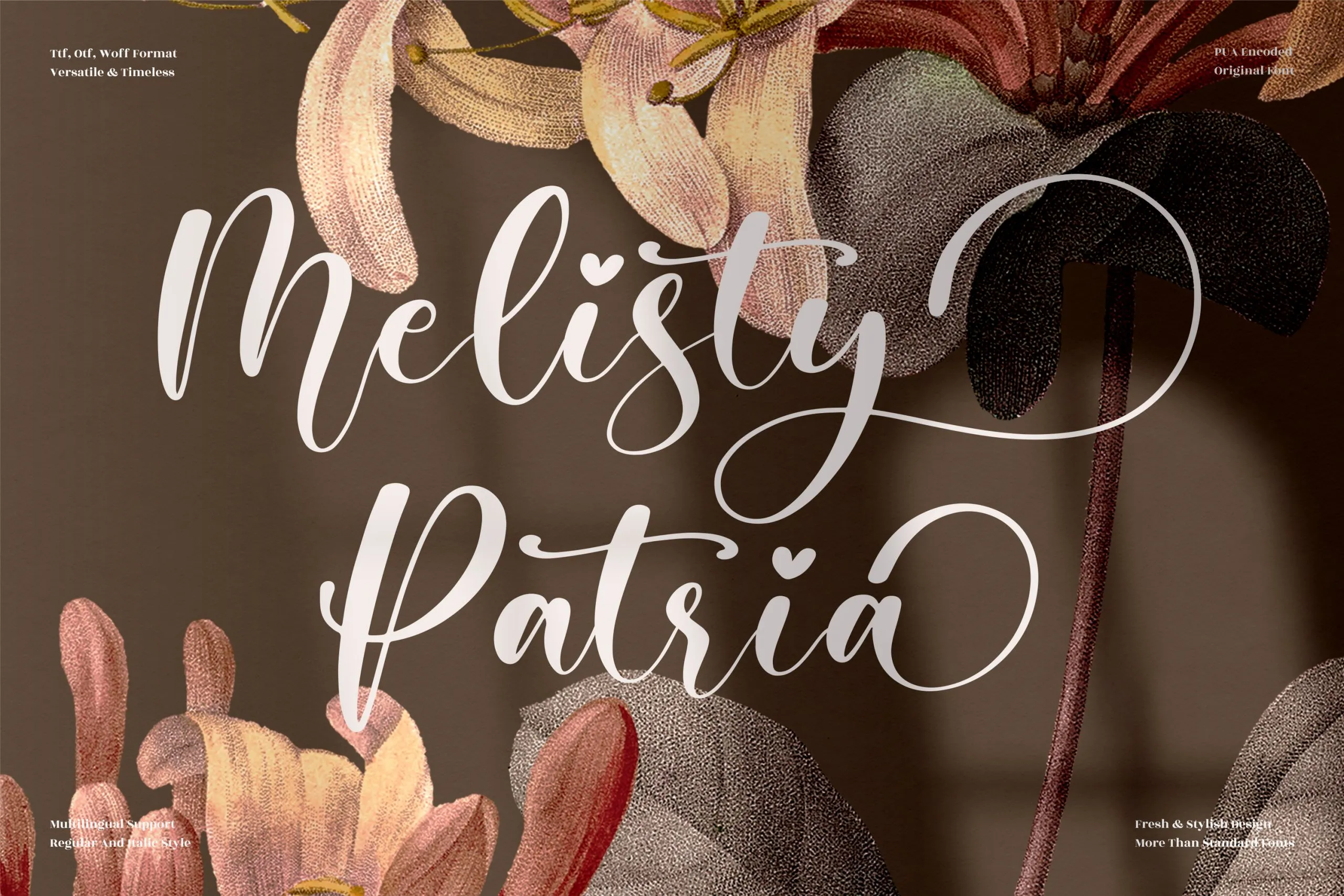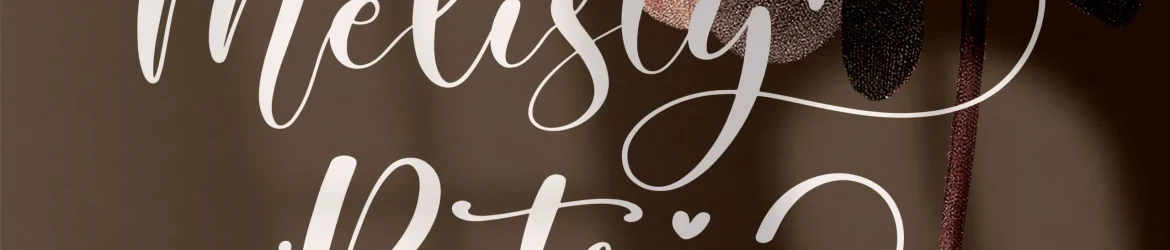
Melisty Patria Font – Download Grátis
A Melisty Patria Font é uma elegante tipografia escrituração perfeita para projetos diversos que exigem uma sensação romântica e encantadora. Suave e detalhada, ela se adequa a um vasto leque de propósitos gráficos, incluindo logotipos, projetos de marca, designs de objetos da casa, embalagens de produtos, prateleiras decorativas, frases inspiradoras, postais, sacolas para compra, camisetas personalizadas, capas de livros, cartões de convite, cartas festivas e etiquetas. Esta fonte também é perfeita para qualquer aplicação que necessite de uma escrituração encantadora, como marcas d’água, eventos especiais ou simplesmente aquelas criações onde você deseja adicionar um toque único e sofisticado à sua produção visual. Seja para projetos profissionais ou pessoais, a Melisty Patria Font certamente enriquecerá seu design.